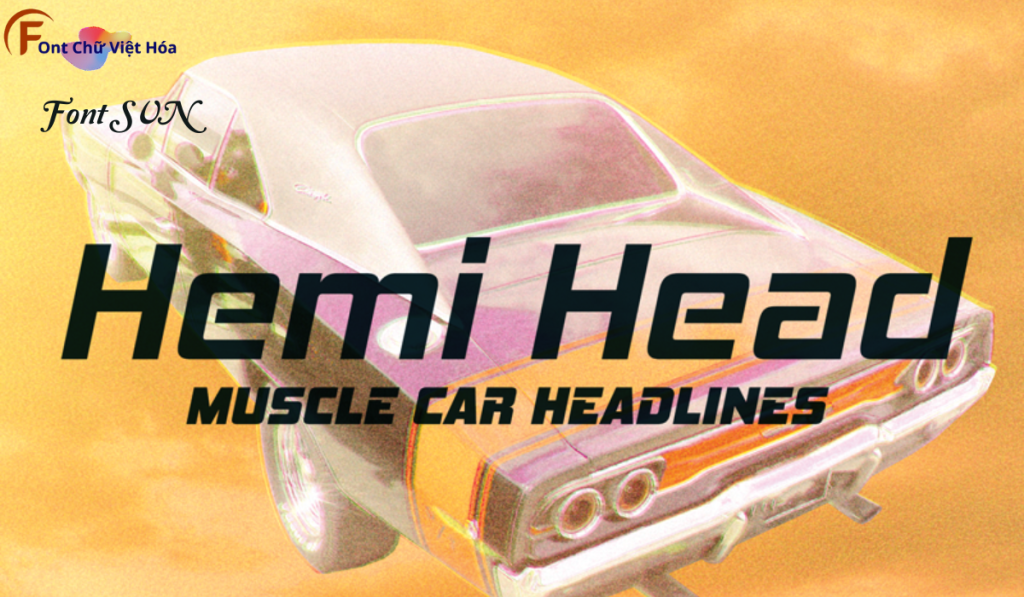
Font SVN Hemi Head Việt Hóa
Font SVN Hemi Head Việt Hóa là một font chữ không chân mạnh mẽ, thuộc bộ font SVN. Được thiết kế với mục tiêu mang lại sự nổi bật và ấn tượng, font này lý tưởng cho các dự án thiết kế như tiêu đề, quảng cáo, và bao bì sản phẩm. Với các nét chữ đậm và chắc chắn, Font SVN Hemi Head Việt Hóa không chỉ dễ đọc mà còn tạo cảm giác mạnh mẽ và quyết đoán. Việc Việt hóa font giúp người dùng dễ dàng sử dụng trong các thiết kế tiếng Việt, mang lại sự tiện lợi và thẩm mỹ cao.